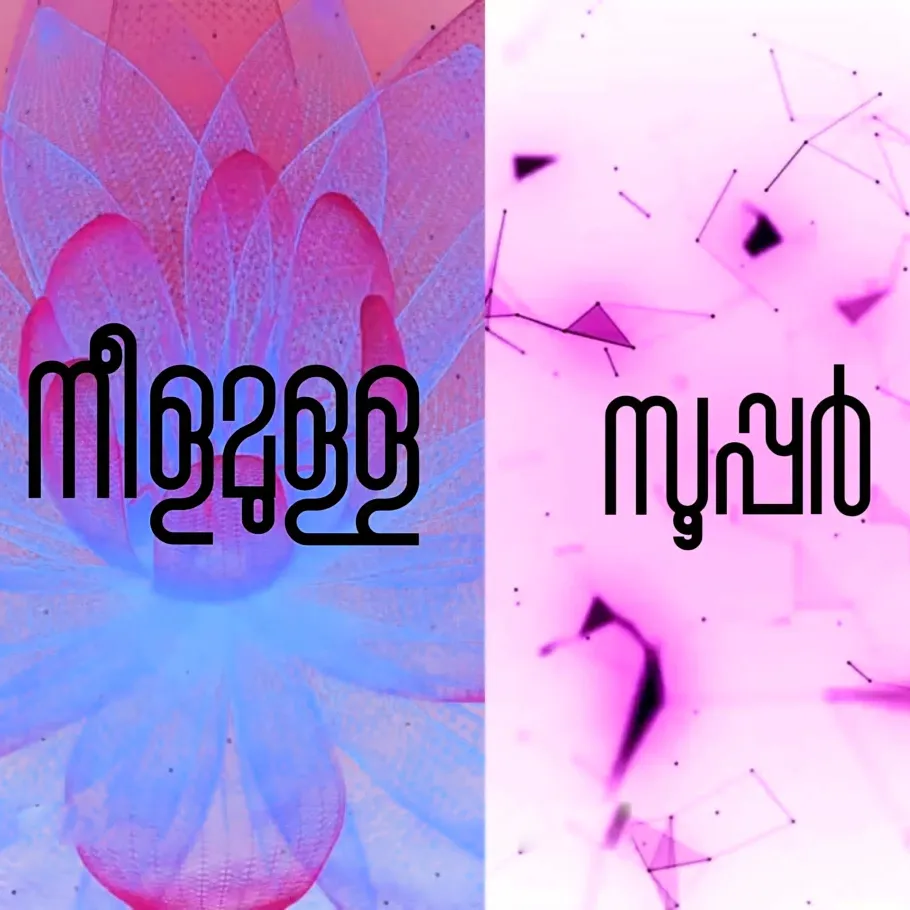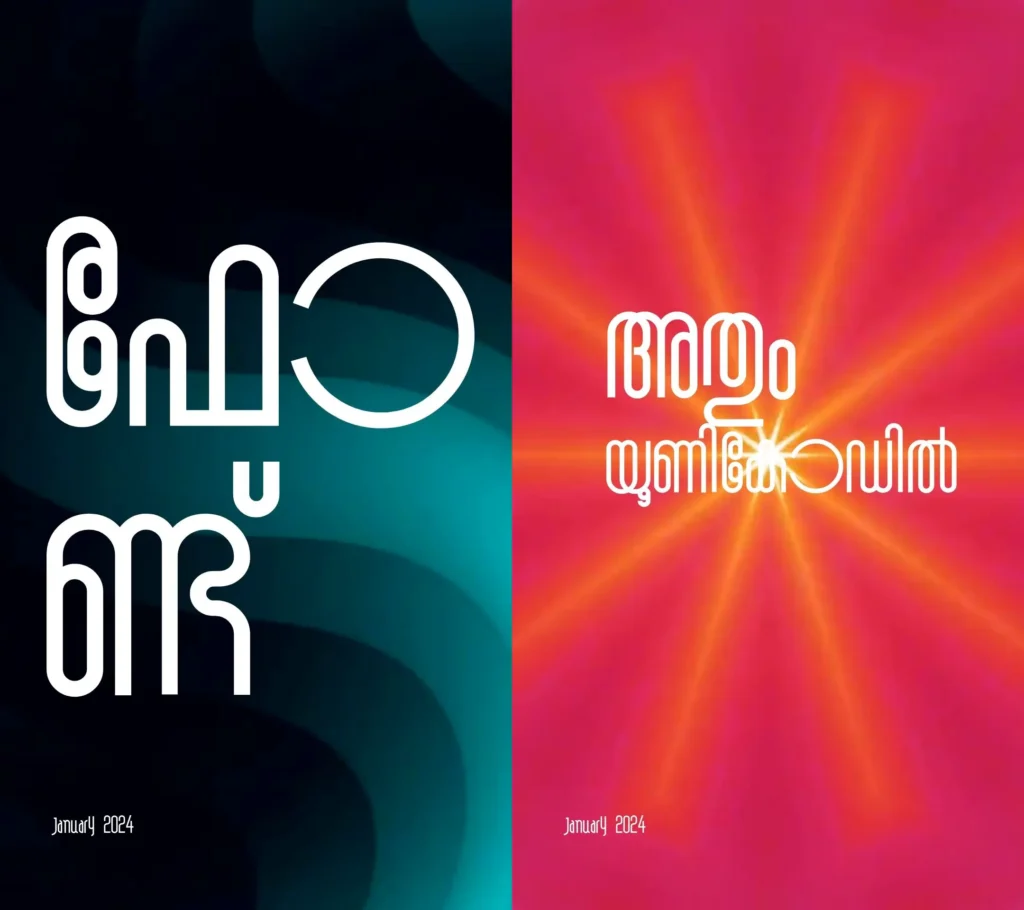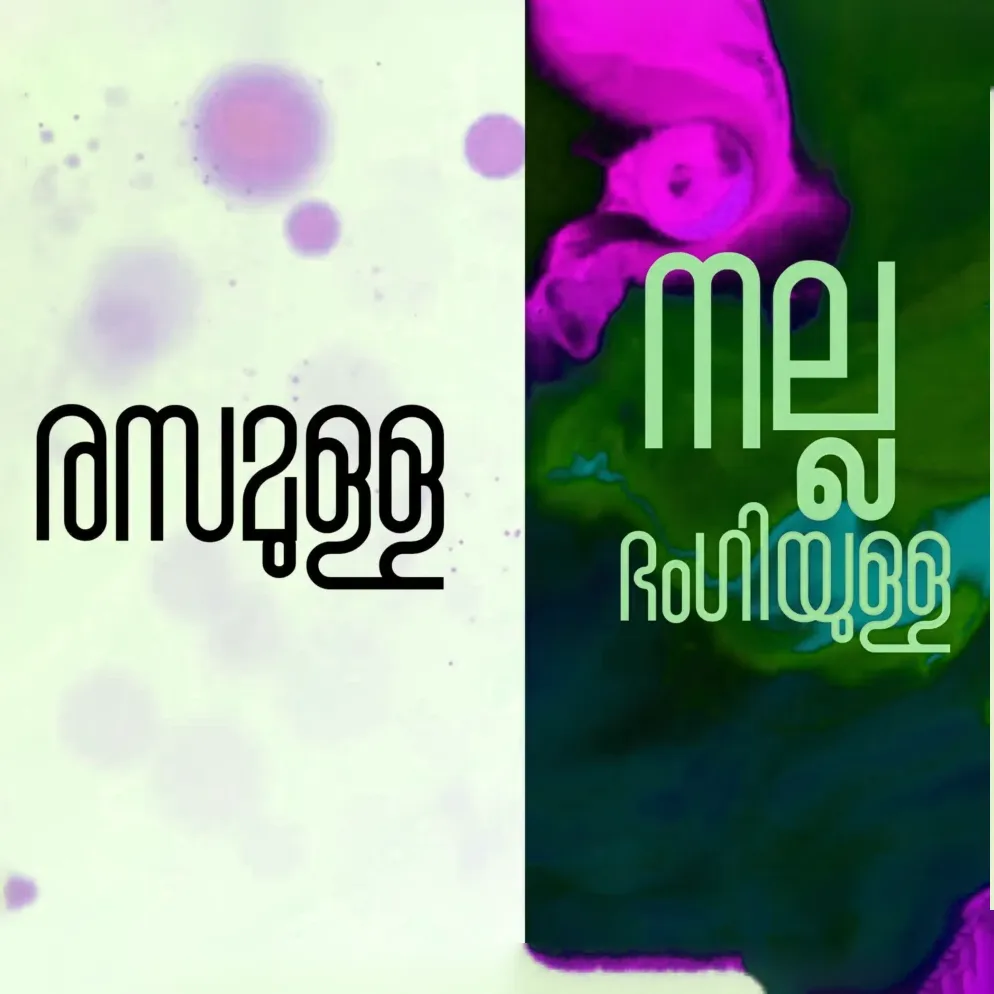
RIT-Chingam | Traditional Malayalam Display Font by Bhattathiri
മലയാളം കാലിഗ്രാഫി രംഗത്തെ കുലപതിയായ നാരായണ ഭട്ടതിരി (Narayana Bhattathiri) രൂപകല്പന ചെയ്ത്, രചന ഇൻസ്റ്റിറ്റ്യൂട്ട് ഓഫ് ടൈപ്പോഗ്രാഫി (RIT) 2024-ൽ പുറത്തിറക്കിയ മനോഹരമായ ഒരു ഡിസ്പ്ലേ ഫോണ്ടാണ് RIT-Chingam. മലയാളം പരമ്പരാഗത ലിപിയിൽ (Traditional Script) അധിഷ്ഠിതമായ ഈ ഫോണ്ട് അക്ഷരങ്ങളുടെ തനിമ ഒട്ടും ചോർന്നുപോകാതെ നിങ്ങളുടെ സൃഷ്ടികൾ ഡിജിറ്റൽ ലോകത്തേക്ക് കൊണ്ടുപോകുന്നു.
പ്രത്യേകതകൾ:
Designer's Masterpiece: കാലിഗ്രാഫർ നാരായണ ഭട്ടതിരിയുടെ വേറിട്ട അക്ഷര ശൈലിയാണ് ഈ ഫോണ്ടിന്റെ ഏറ്റവും വലിയ ആകർഷണം.
Stylistic Alternates: ഒരേ അക്ഷരത്തിന് തന്നെ വ്യത്യസ്തമായ രൂപങ്ങൾ (Alternates) ഈ ഫോണ്ടിൽ ലഭ്യമാണ്. ഇത് ഡിസൈനുകൾക്ക് കൂടുതൽ ക്രിയേറ്റീവ് ലുക്ക് നൽകാൻ സഹായിക്കുന്നു.
Narrow & Wide Contrast: വീതി കുറഞ്ഞ (Narrow) ചില അക്ഷരങ്ങൾ സവിശേഷമായ ഒരു ശൈലി നൽകുകയാണ് ഇവിടെ. ഇത് ടൈപ്പോഗ്രാഫിയിൽ ഒരു വേറിട്ട അനുഭവം നൽകുന്നു.
Modern Traditionalism: പരമ്പരാഗത ലിപി ഇഷ്ടപ്പെടുന്നവർക്കും എന്നാൽ ആധുനികമായ ഡിസ്പ്ലേ രീതികൾ വേണ്ടവർക്കും ഒരേപോലെ തിരഞ്ഞെടുക്കാവുന്നതാണ് ആർ.ഐ.ടി ചിങ്ങം.
സിനിമ ടൈറ്റിലുകൾ, പുസ്തകങ്ങളുടെ കവർ പേജുകൾ, പ്രത്യേക ആഘോഷങ്ങൾക്കുള്ള പോസ്റ്ററുകൾ എന്നിവയ്ക്ക് ഈ ഫോണ്ട് തികച്ചും അനുയോജ്യമാണ്.